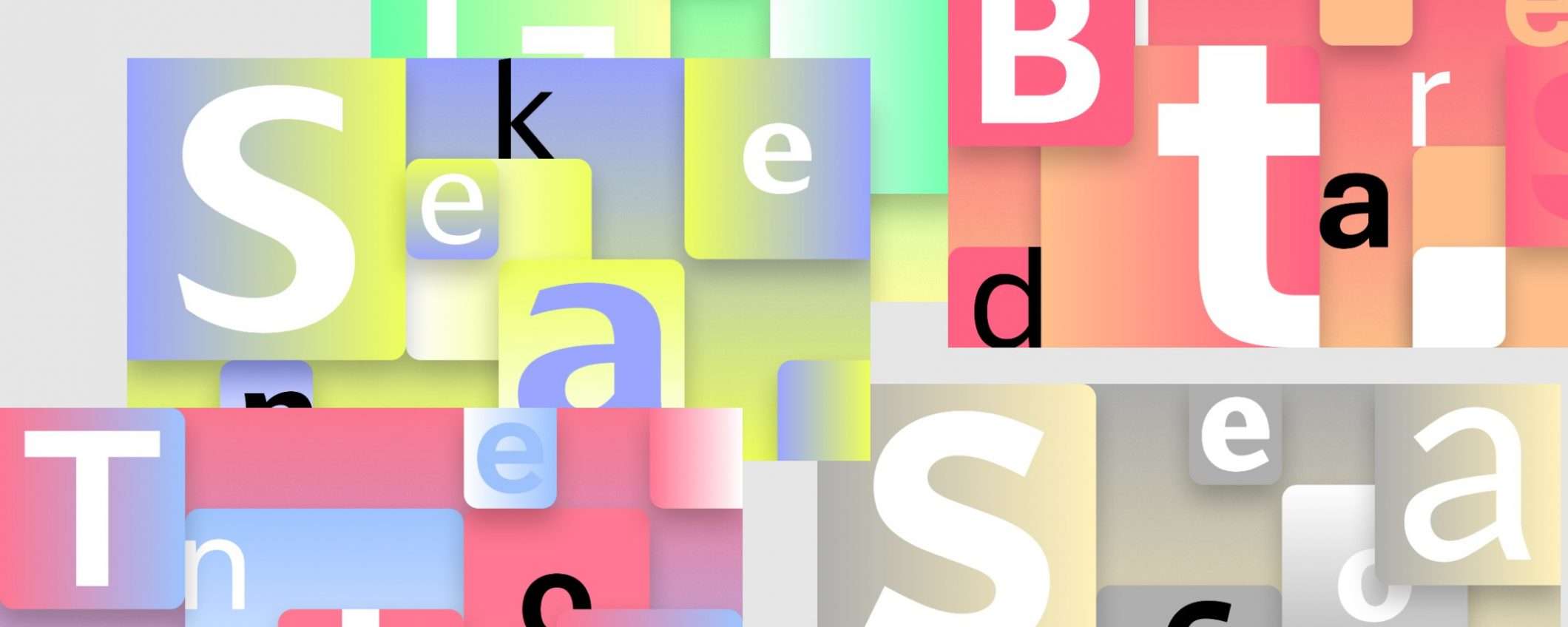
Addio Calibri! A partire dal 2022, Microsoft abbandonerà quello che è stato per lunghissimo tempo il font predefinito della propria suite Office. Ancora non si sa, però, quale sarà il sostituto. Microsoft ha commissionato lo sviluppo di 5 nuovi font, tra i quali scaturirà nei prossimi mesi il prescelto per diventare la veste ufficiale delle app Office (Microsoft 365) a partire dall’anno venturo.
Questi i font candidati:
- Tenorite (di Erin McLaughlin e Wei Huang)
- Bierstadt (di Steve Matteson)
- Skeena (di John Hudson e Paul Hanslow)
- Seaford (di Tobias Frere-Jones, Nina Stössinger e Fred Shallcrass)
- Grandview (di Aaron Bell)
Microsoft ha spiegato nel proprio post di annuncio che l’importanza del font standard è tutto fuorché formale: così come con il passaggio dal Times New Romans al Calibri, anche il passaggio dal Calibri al prossimo font rappresenterà un nuovo cambio di veste e ciò significa un impatto differente con l’utente che entra nelle app. Il font standard è causa della “prima impressione", definisce il carattere del prodotto e non può essere sottovalutato.
Ecco perché il gruppo di Redmond ha commissionato cinque nuove produzioni che mette ora a disposizione tramite i servizi cloud: i dati di utilizzo saranno valutati nei mesi a venire, fino ad arrivare alla scelta conclusiva che caratterizzerà l’impatto grafico di Office per i prossimi (15?) anni.